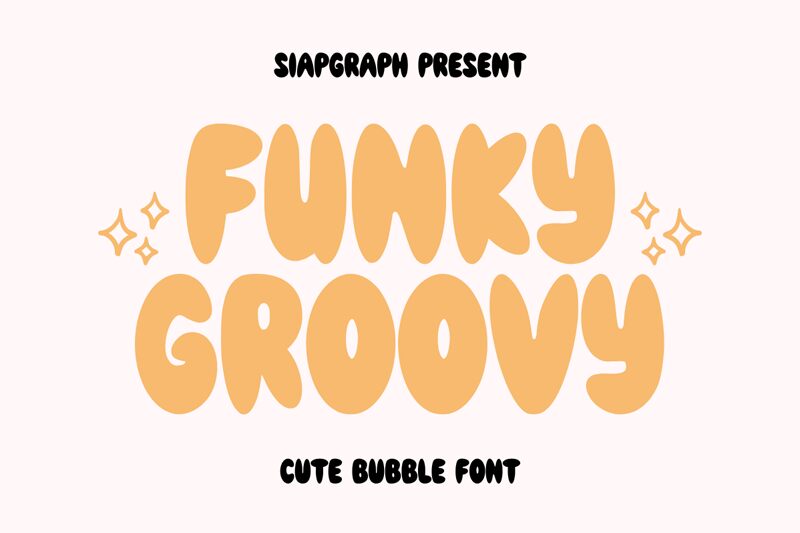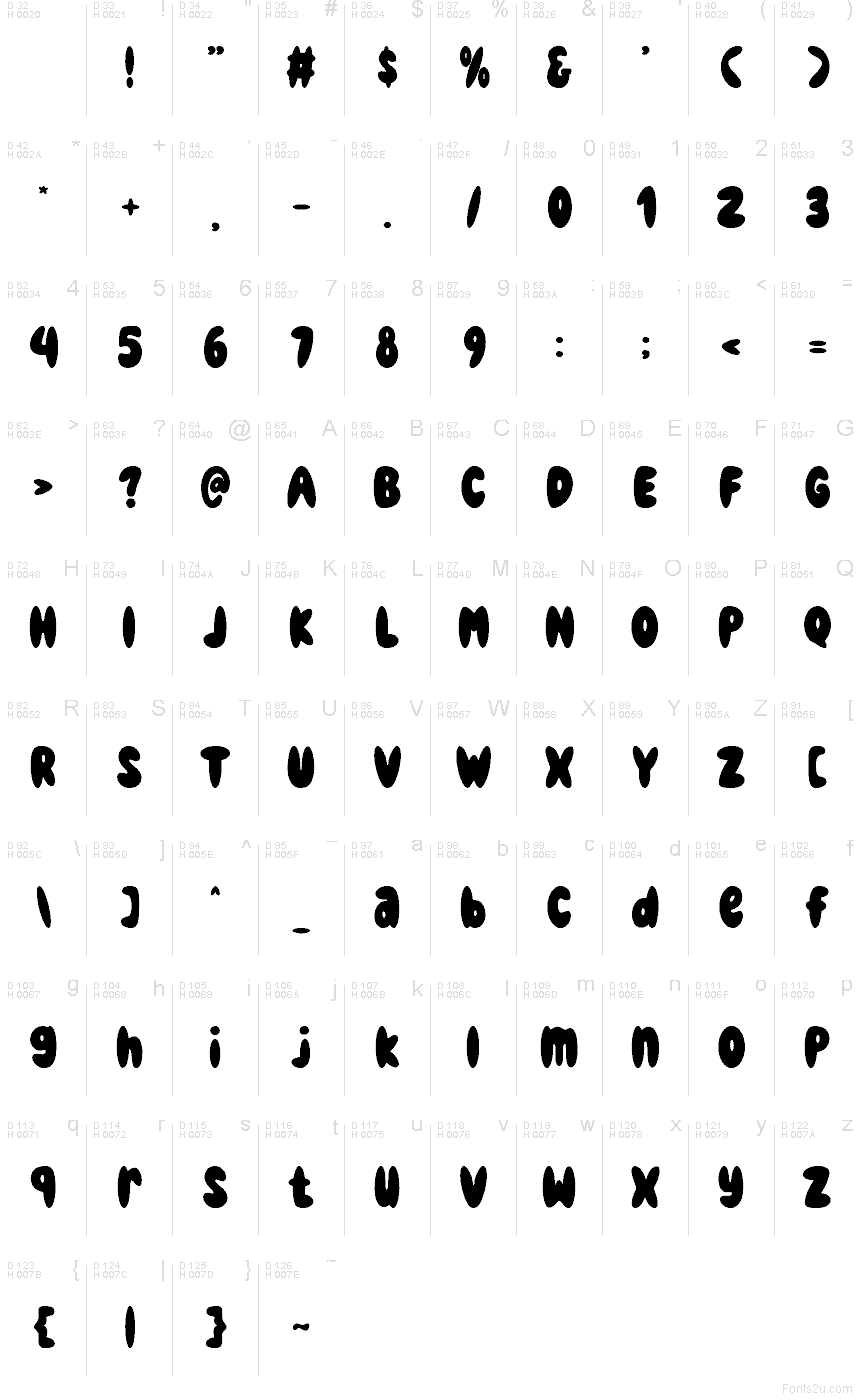
Funky Groovy
Funky Groovy от SIAPGRAPH STUDIO - это бесплатный мультяшный дисплейный шрифт, состоящий из пухлых, округлых силуэтов, которые придают буквам мягкий и прыгучий вид. Формы сохраняют плотный черный вес, а суженные соединения и плавно опускающиеся кривые создают ощущение расслабленного, почти «плавящегося» ритма.
Эта подчеркнутая пышность делает шрифт идеальным для коротких заголовков на детской упаковке, стикерах, приглашениях, постах в соцсетях и креативных вывесках. Он также отлично подойдет для постеров и обложек для YouTube, где крупные округлые формы должны в первую очередь передавать характер, а не просто считываться как текст.